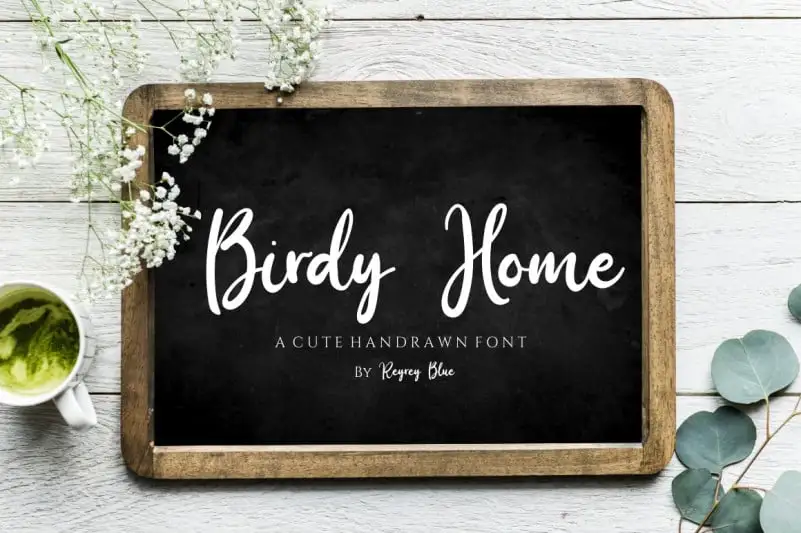
Birdy Home Script Font – Download Grátis
Agora é a hora de adicionar um toque delicado e moderno à sua identidade visual com a Fonte Birdy Home Script de ReyreyBlue. Esta elegante tipografia script vem equipada com swashes no início e fim que trazem uma sensação única ao seu design, complementando perfeitamente qualquer projeto gráfico. Ideal tanto para as marcas sofisticadas quanto para cartões personalizados ou mensagens de boas-vindas, a Fonte Birdy Home Script é uma escolha inspiradora para projetos que valorizam um visual cuidadoso e criativo. Ela será perfeita para branding moderno, criações de logomarca, embalagens de produtos, cartões personalizados, frases escritas à mão ou até mesmo editoriais de convites, estabelecendo uma atmosfera suave e atraente em qualquer projeto que você possa criar. Transforme sua marca de forma única com Birdy Home Script.